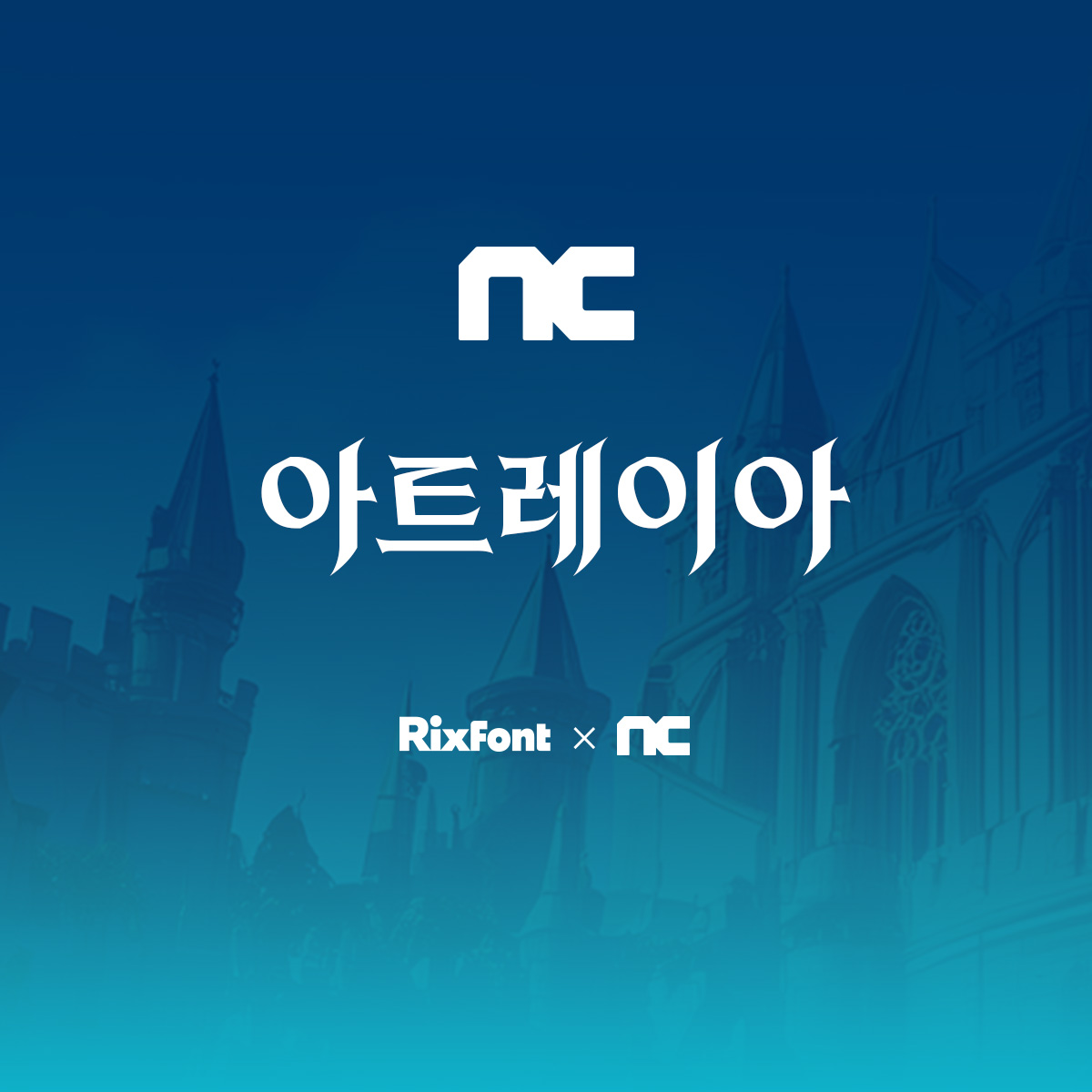
유려한 곡선과 날카로운 세리프 - 아이온2 아트레이아체
아트레이아체는 멀티 글리프를 적극적으로 활용한 것이 특징입니다.
기본 폰트에서는 가독성을 확보하고, 짧은 문구나 연출용 타이틀에서는 멀티 글리프를 통해 판타지 게임 특유의 분위기를 보다 화려하게 표현할 수 있도록 기획하였습니다. 상황에 따라 서로 다른 표정을 가질 수 있는 폰트를 목표로 했습니다.
| 스펙 | 1종 Bold (한글 11,172자) 2종 Light, Medium(한글 2,500자 + 영문 94자 + 약물 986) |